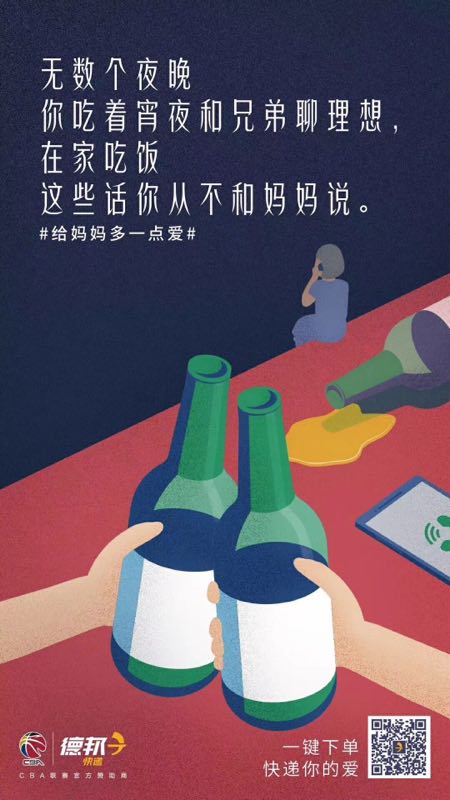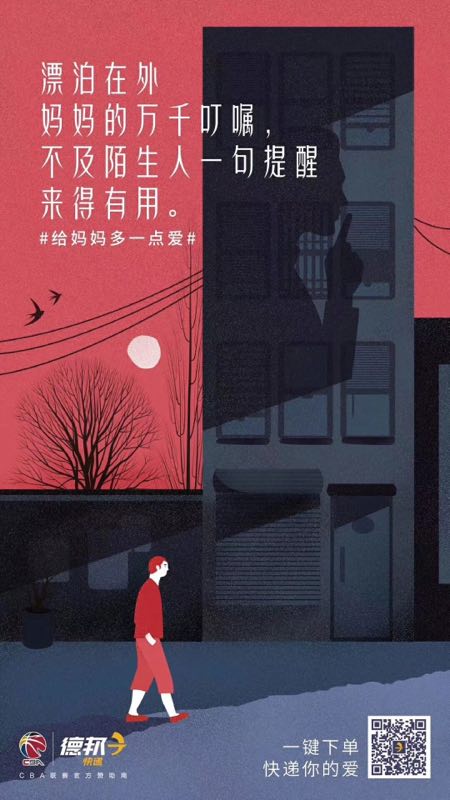
方正非凡体家族
郭炳权
创意字体
通常字形中的点、撇、捺、钩、提等笔画各具面目,但方正非凡体只用了矩形与弧尖两种图形元素来构建,把这些笔画概括为飘逸的弧形,并且使左右舒展的笔画尽量对称,最大限度地简化笔画造型。方正非凡体家族包含6款字重,其字形颀长,个性简静柔美,宛若身形窈窕、气质不凡的女子,适用于女性时尚类品牌的广告和产品包装设计。